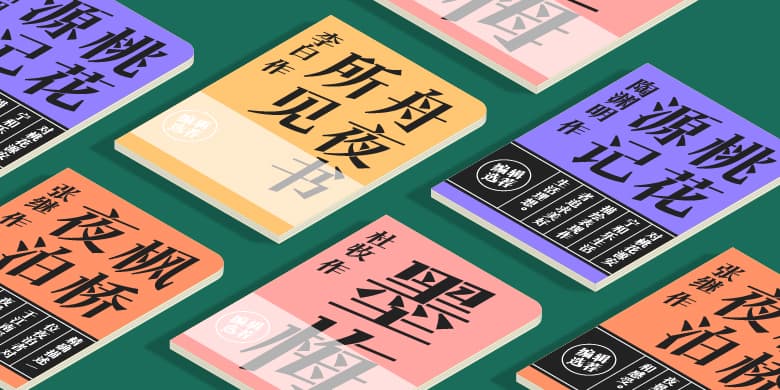
品牌:方正字库设计师:倪初万发行时间:2020字库编码:大陆简体(GB2312-80)分类:创意字体字体属性:精品字
风入松体是宋体字的传承与进化,文字笔画的衔接和交叉处给人的视觉反应就是堆墨,镂空的方式本身就很有趣,让这款字体白区贯通,更加透气,象风入松一样高雅灵动,9度的右上倾斜,提振精神,感觉很爽!该字体的应用更侧重于标题字,也许能够起到画龙点睛的作用。